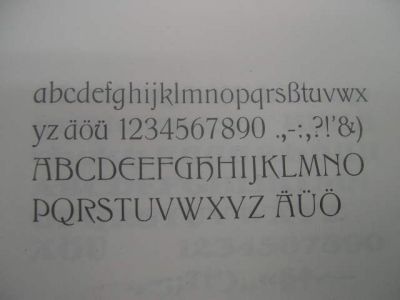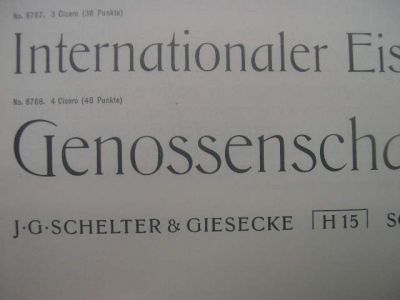
Borghese alias Vienna?
Hier meint der digitale Fachmann, dies sei eine Schrift namens Vienna, die es wohl auch heute noch in digitaler Form gibt.
Ich habe sie nun belegbar gefunden:
Borghese
Schelter & Giesecke, Leipzig
Erstguß 1904
Hausschrift mit Gußmarke
Schön? Schön.
Quellen:
Georg Kandler, Erinnerungen an den Bleisatz, Band 2, seite 41
Schelter & Giesecke Hauptprobe, Seite H15
So steht's auch bei myfonts:
Vienna
This early 1900s type is from the German foundry of Schelter & Gieseke, and is typical of early twentieth century design.
Ja, aber bei Schelter heißt sie Borghese.
Nicht unüblich: Vielleicht wurde sie von einer oder mehreren Schriftgießereien mitvertrieben und dann unter anderem Namen?
Und "early 1900s ... "? Pffffttt...
Ein Erstguß-Jahr ist ein Erstguß-Jahr.
Alles andere ist unbefriedigend.
Aber das wichtigste ist, daß ich einen vollständigen Zeichensatz von dieser Schrift habe. Ich weiß ja selbst, daß die Jugendstil-Schriften so speziell sind, daß man sie bei weitem nicht für viele Anlässe nutzen kann. Aber denen gehört mein ganzes Herz.
Hatten wir hier nicht irgendwo schon mal das Thema, dass von einer Schrift am ehesten noch der Name zu schützen sei? Ist das vielleicht der Grund?
Ich weiß leider nichts über das Markenrecht Anfang des 20. Jahrhunderts.
In den 1930er Jahren war das nicht ungewöhnlich:
Eigentlich kann es nur so sein, daß diese Vermarktung in gegenseitiger einvernehmlicher Absprache erfolgte.
Um die Jahrhundertwende zuvor muß es anders gewesen sein.
Ich denke, das war eine Modeerscheinung um die Jahrhunderwende herum. Sie haben oft diese überproportional großen Rundbögen im Versal-R und oft auch unter die Schriftlinie rutschende Abstriche bei eben diesem R.